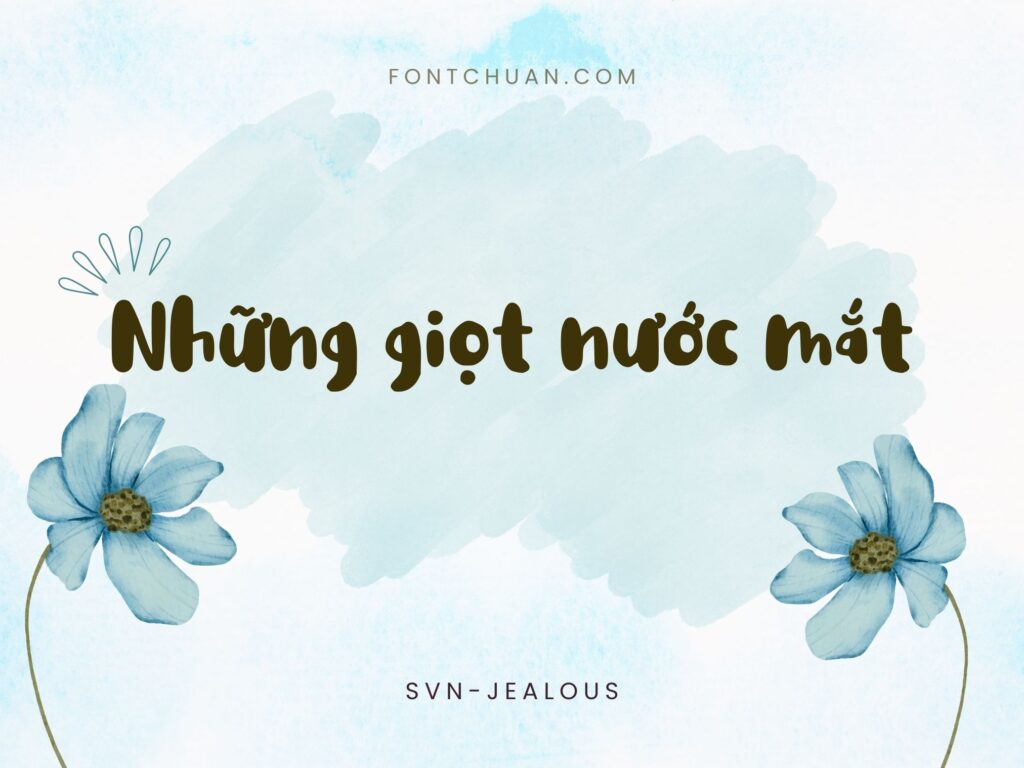
Font SVN Jealous Việt Hóa
Font SVN Jealous là phiên bản Việt hóa của kiểu chữ Jealous, được thực hiện bởi STYLEno.1 Fonts. Jealous là một font chữ viết tay đáng yêu, đơn giản và đa dụng, phù hợp cho nhiều dự án như sách thiếu nhi, trích dẫn, logo, tiêu đề và nhiều hơn nữa. Font này mang đến cảm giác vui tươi và thân thiện, giúp thiết kế của bạn trở nên sinh động và hấp dẫn hơn.
SVN Jealous lý tưởng cho các dự án thiết kế yêu cầu sự vui nhộn và thân thiện, như thiết kế sách thiếu nhi, thiệp mời, logo thương hiệu và các ấn phẩm truyền thông. Các ngành nghề như giáo dục, quảng cáo và ẩm thực có thể tận dụng font này để tạo điểm nhấn trong thiết kế. Ngoài ra, font cũng thích hợp cho các sự kiện như Sinh nhật, Tết, Giáng sinh và các lễ hội khác.